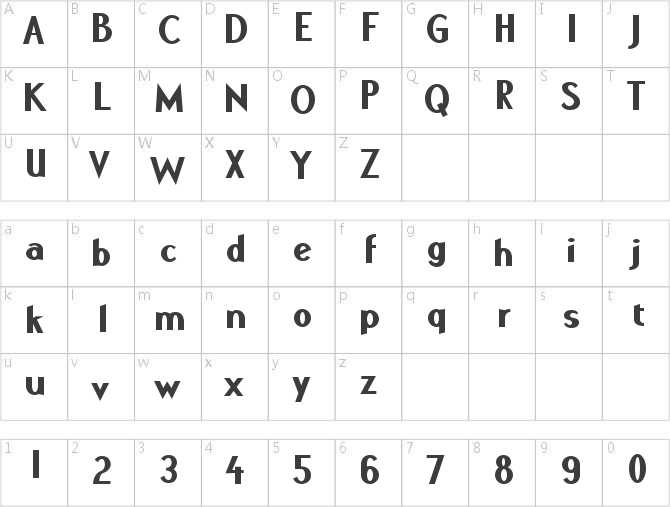
Cool Weekdays Bold Demo
Cool Weekdays Bold Demo介绍
Cool Weekdays Bold Demo字体字库是一款让人赏心悦目、百看不厌的英文字体,适合各类广告和产品包装设计应用,字体大小0.03MB,格式为ttf字体,上传用户是23KUN,作者/版权方为未知